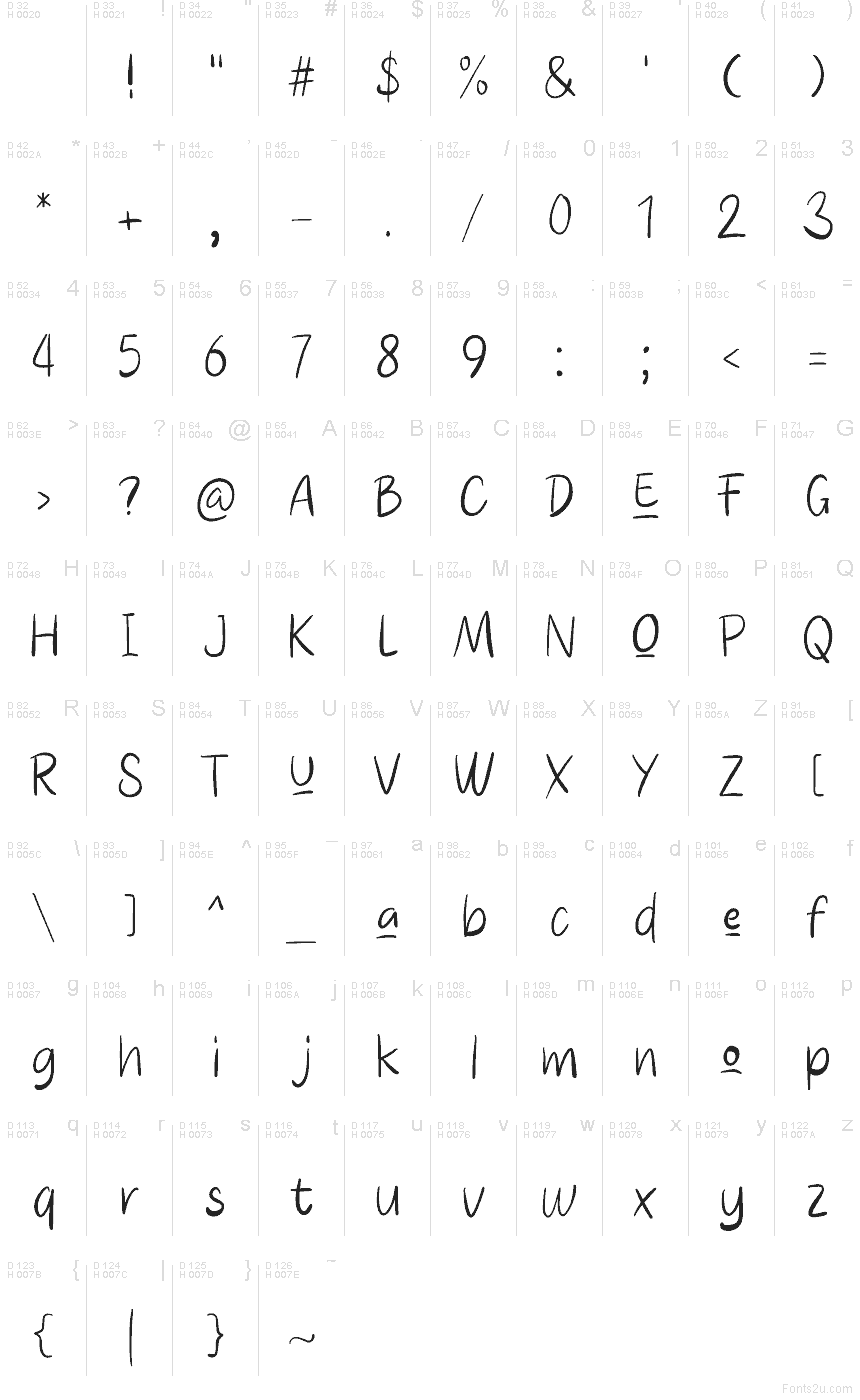
Rebel Produktif
Rebel Produktif від Hello Good Studio — це безкоштовний рукописний шрифт із вільними штрихами, що нагадують роботу маркером. Високий та нерівний ритм надає літерам енергійного, мальованого характеру. Форми прості й відкриті, із закругленими закінченнями та невеликими розривами, завдяки чому шрифт не виглядає занадто вилизаним.
Rebel Produktif чудово підійде для ескізів логотипів, заголовків на плакатах, графіки для соціальних мереж, карток із цитатами та неформального брендингу, де доречна легка особиста нотка. Його невимушена форма також добре виглядає на етикетках, наклейках та в коротких редакційних акцентах, зберігаючи автентичність ручної роботи без зайвого хаосу.